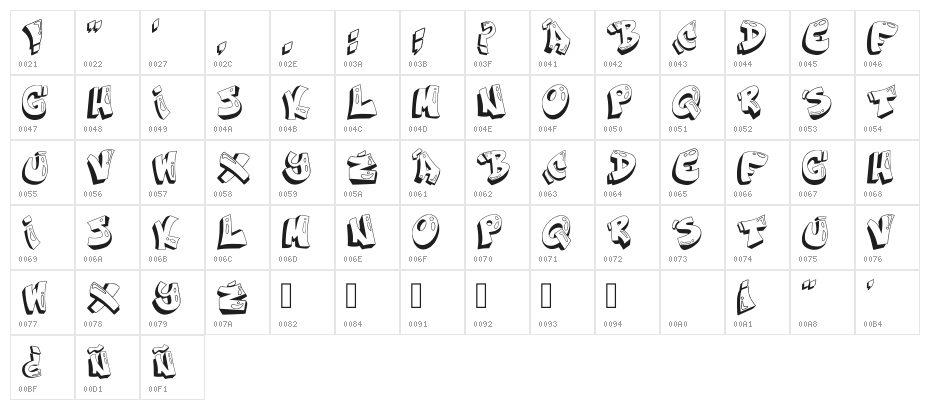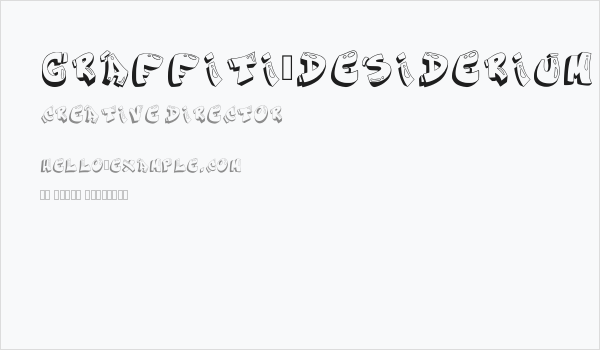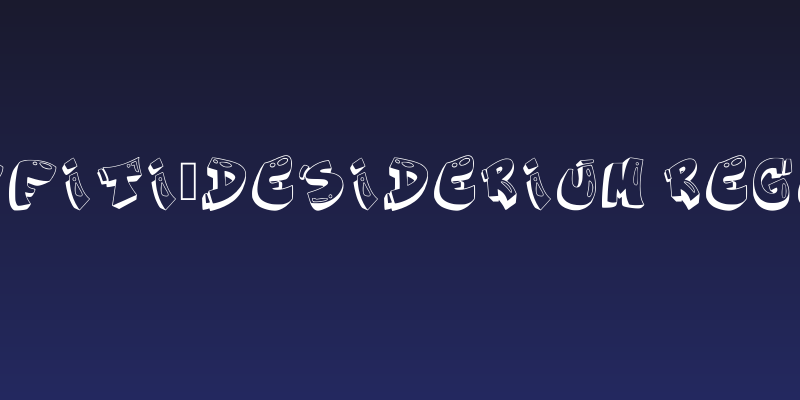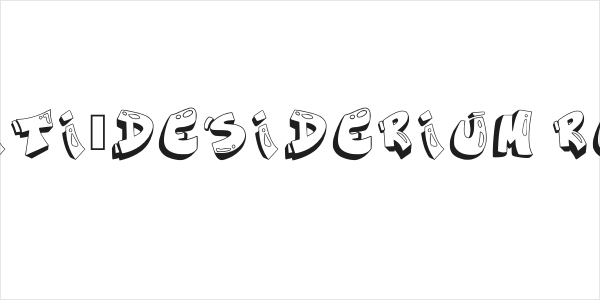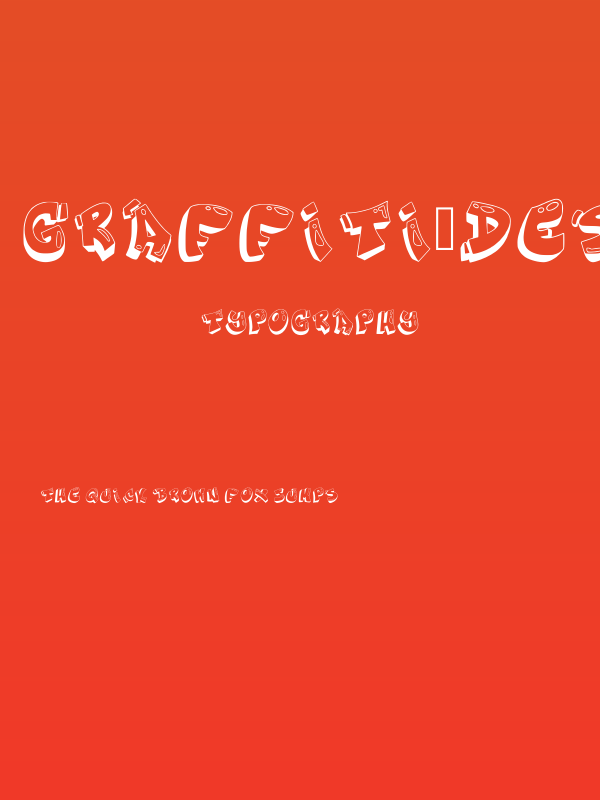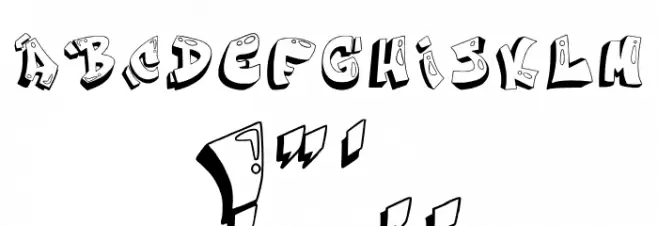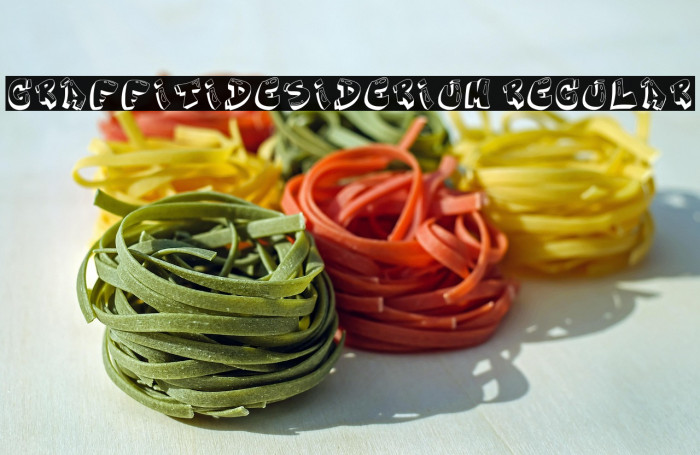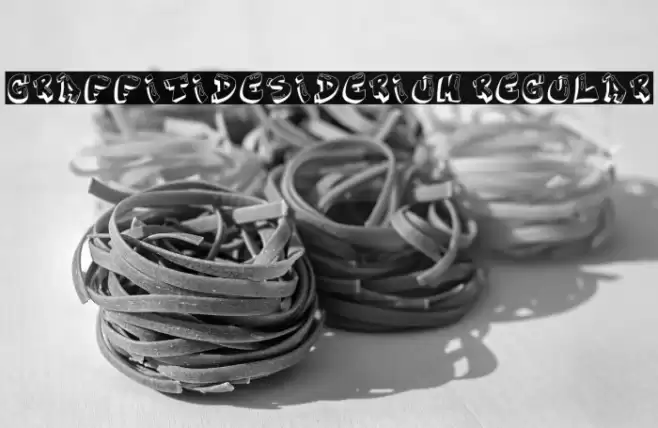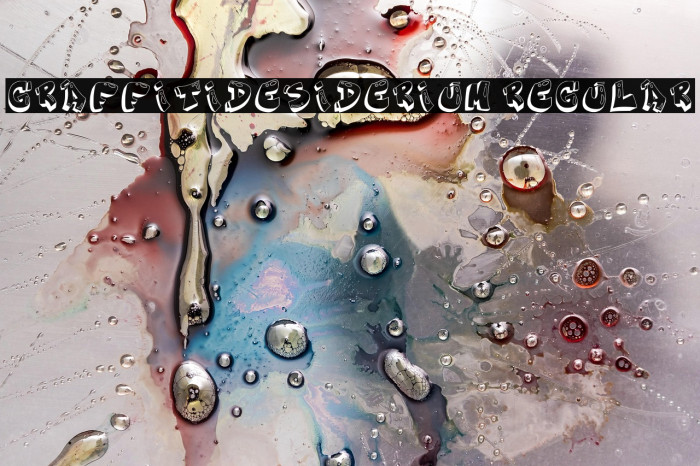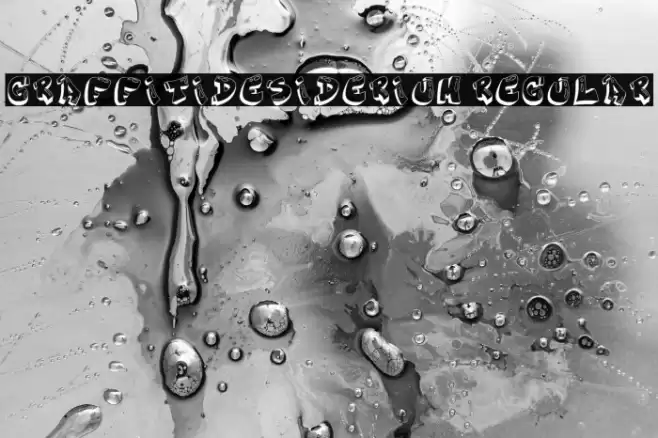
Graffiti_desiderium Regular Font
| Schriften Familie | Graffiti_desiderium |
| Kategorien | Graffiti |
| Breite | Expanded |
| Gesamtstil | Modern, Urban |
| Vorgeschlagene Projekte | Perfect for street art-inspired designs, music album covers, urban-themed posters, and creative branding projects. |